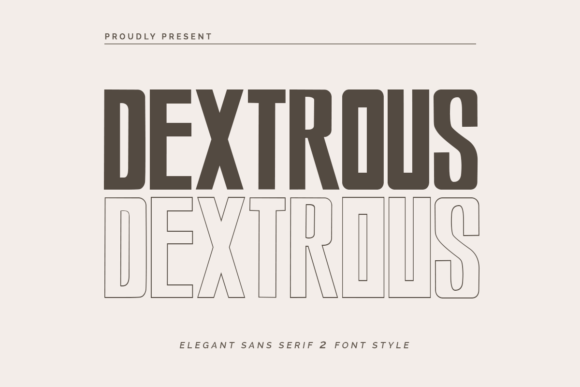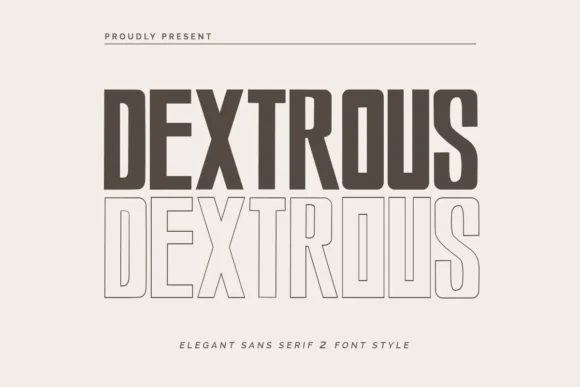
Dextrous - это современный, чистый и элегантный шрифт без засечек, который обладает широкими возможностями. Он прекрасно подходит для создания престижных логотипов, заголовков и даже красивых свадебных приглашений. Он легко читается и отлично смотрится в любом проекте.